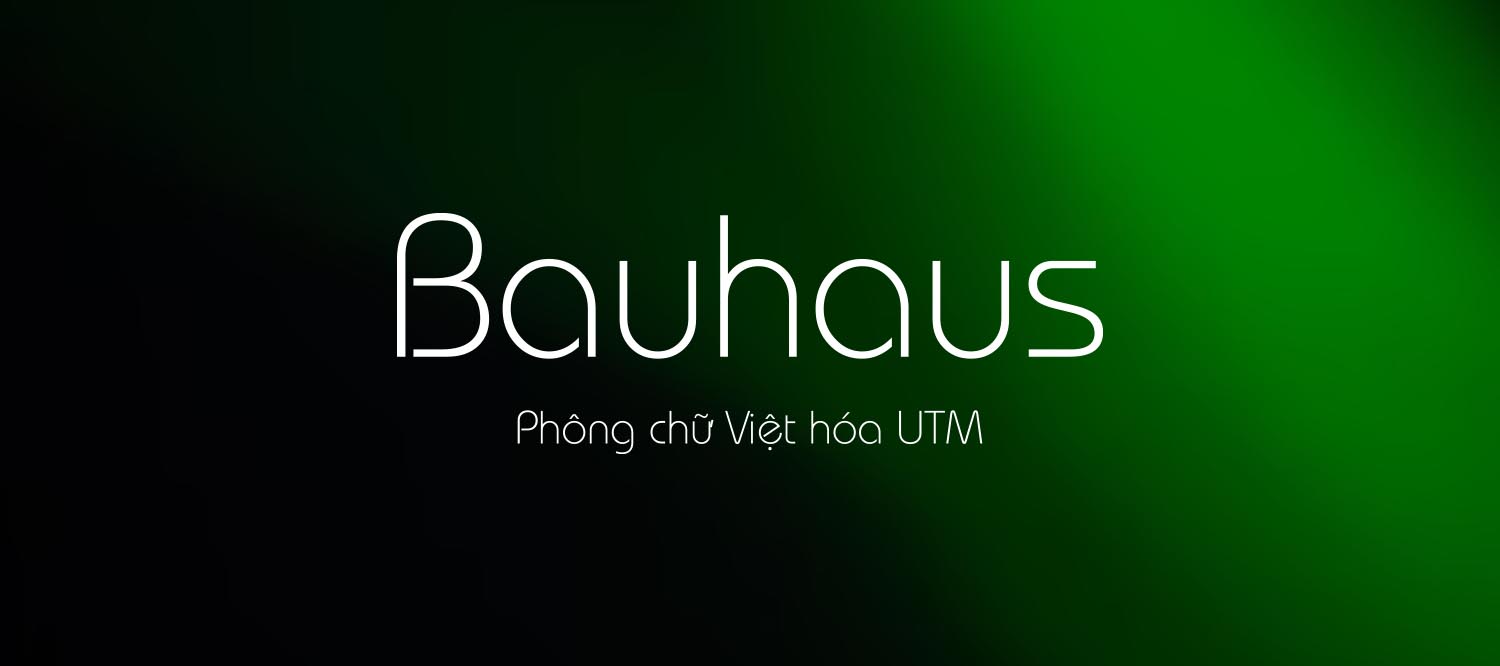
![[Tải Miễn Phí] Font Chữ Bauhaus Việt Hóa Chuẩn](https://cdn.s99.vn/cloud/font-chu-UTM-Bauhaus-Light-viet-hoa-anh-5.jpg)
Phong trào thiết kế Bauhaus xuất hiện vào đầu thế kỷ 20 tại Đức, được xem là cái nôi của trường phái thiết kế hiện đại. Nguyên lý của Bauhaus là tính tối giản, cân đối hình học và không trang trí rườm rà. Phong cách này đã ảnh hưởng mạnh mẽ đến thế giới typography.
Font Bauhaus mang những đặc trưng dễ nhận biết như:
Đường nét hình học: tròn, vuông, đơn giản
Cấu trúc rõ ràng, dễ đọc
Font sans-serif (không chân), hiện đại và tính ứng dụng cao
Tuy nhiên, nhiều font Bauhaus gốc chưa hỗ trợ đầy đủ tiếng Việt. Font Bauhaus Việt hóa chính là phiên bản đã được chỉnh sửa để bao gồm các dấu thanh và ký tự đặc trưng như: ă, â, ê, ô, đ... Việc Việt hóa giúp người dùng tự tin áp dụng trong các dự án thiết kế tại Việt Nam.
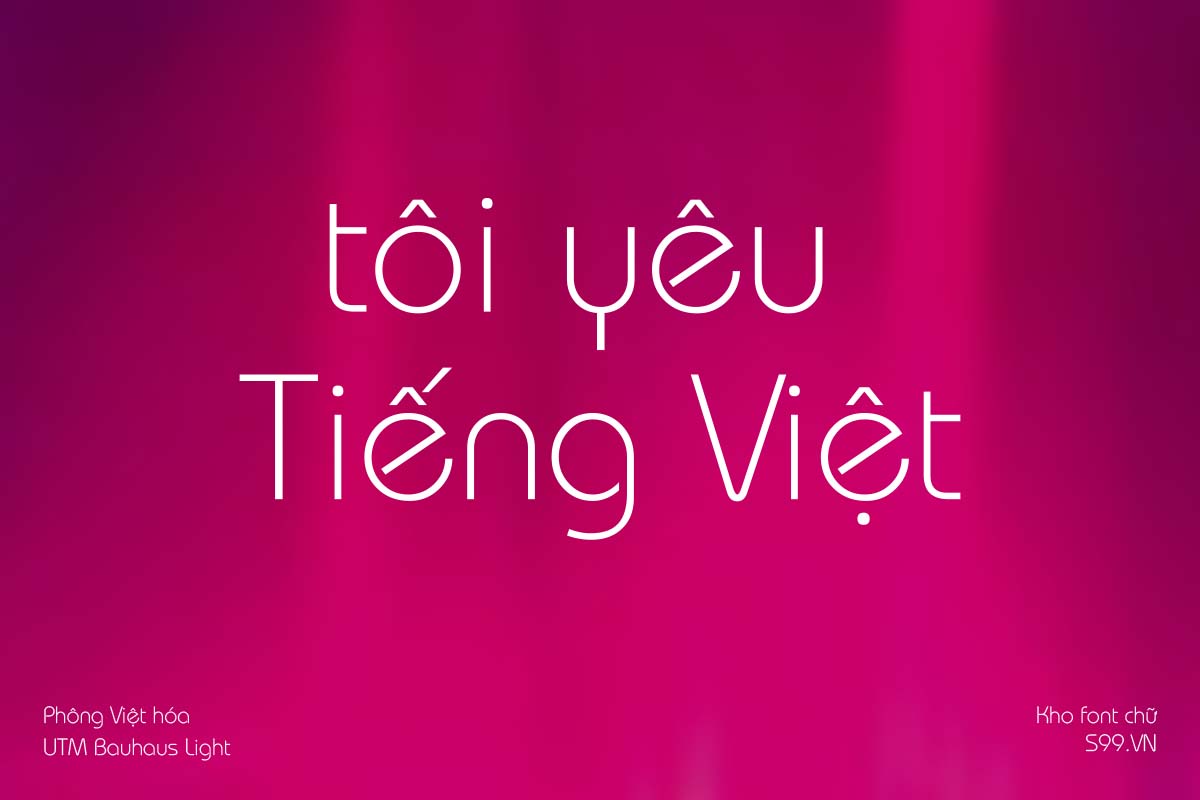
Trong thiết kế ấn phẩm tiếng Việt, việc font chữ hỗ trợ đầy đủ các dấu thanh là yêu cầu cần thiết. Phần lớn các font quốc tế chưa có hỗ trợ Unicode đầy đủ cho tiếng Việt, khi sử dụng sẽ dẫn đến các lỗi như:
Mất dấu, sai định dạng
Mất cân đối trong bố cục
Không đạt yêu cầu thẩm mỹ trong in ấn
Font Việt hóa giúp khắc phục hoàn toàn các vấn đề trên. Bằng cách thiết kế lại các dấu tiếng Việt đồng bộ với form chữ gốc, font sẽ trở nên thích hợp với người dùng Việt Nam.
Ngoài ra, một số tác giả tại Việt Nam đã thực hiện Việt hóa font Bauhaus như: Nhóm Online Fonts, Font TH của S99, SVN Fonts
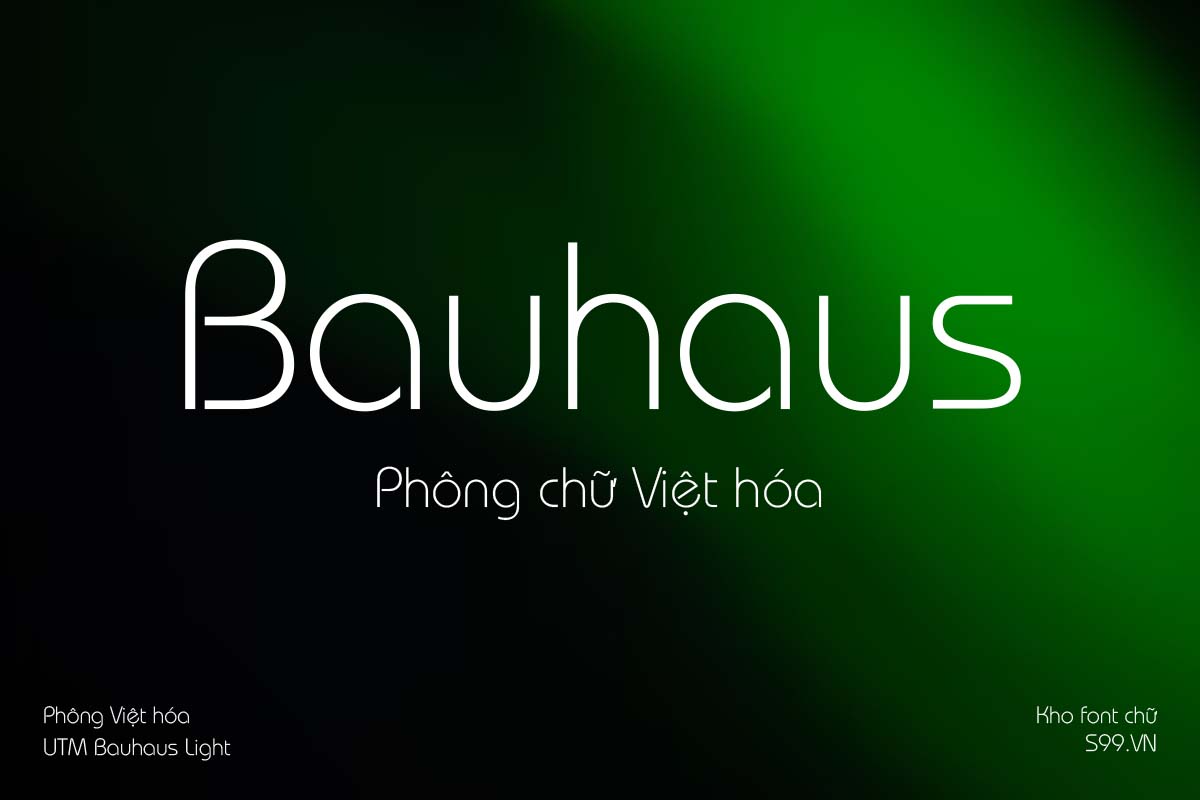
UTM Bauhaus Light là phông chữ không chân (sans-serif) mang đậm tinh thần hình học tối giản của trường phái Bauhaus. Với thiết kế gọn gàng, độ đậm nhẹ và đường nét tròn đều, font này rất lý tưởng cho các tiêu đề, logo giáo dục hoặc thiết kế mang tính học thuật. Bản Việt hóa hỗ trợ đầy đủ dấu tiếng Việt, đảm bảo hiển thị chính xác và đồng bộ trong mọi nền tảng.
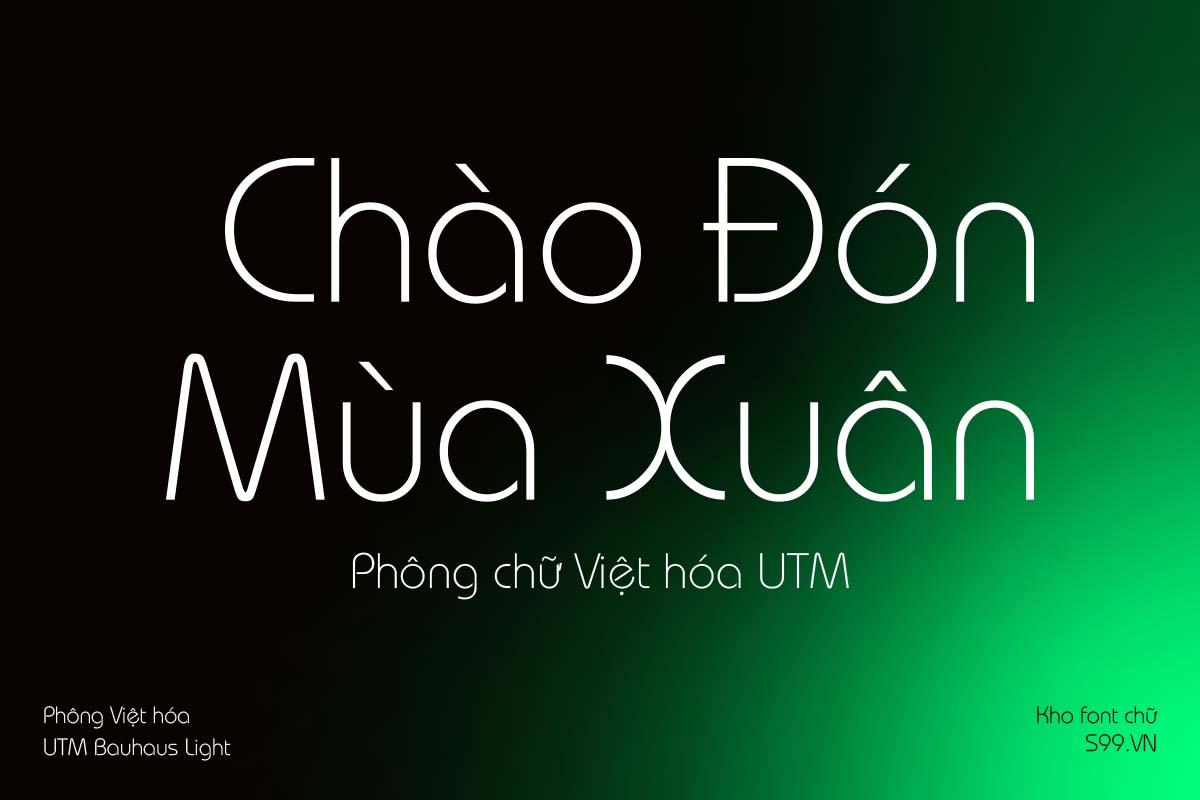
TH Cungcap 11 là font chữ mang cảm giác cứng cáp, mạnh mẽ với form dáng góc cạnh và cấu trúc hình học đậm nét. Font đặc biệt phù hợp với thiết kế poster quảng cáo, tiêu đề game hoặc banner giới thiệu sản phẩm công nghệ. Dù có dáng vẻ công nghiệp, font vẫn giữ được sự rõ ràng và cân đối khi dùng tiếng Việt.
TH Guton là bộ font hiện đại gồm 4 kiểu chữ: Regular, Medium, Bold và Black. Thiết kế dựa trên cấu trúc hình học rõ ràng, font giữ được sự cứng cáp nhưng vẫn mềm mại, thích hợp cho thiết kế UI/UX, in ấn tạp chí, và thương hiệu startup. Việt hóa hoàn chỉnh giúp đảm bảo độ tương thích cao trong mọi nội dung tiếng Việt.
TH Futurama sở hữu thiết kế hiện đại, khỏe khoắn, với các đường cắt sắc nét, phù hợp với lĩnh vực thể thao, giải trí, hoặc công nghệ. Font kết hợp giữa phong cách Bauhaus và yếu tố công nghiệp, mang lại cảm giác vừa chuyên nghiệp, vừa năng động. Bản Việt hóa hỗ trợ đầy đủ dấu, rất lý tưởng cho tiêu đề quảng bá.
Metropolis là font sans-serif kinh điển theo phong cách Bauhaus hiện đại, nổi bật với cấu trúc hình học rõ ràng, mạnh mẽ. Bộ font bao gồm tới 18 biến thể từ Thin đến Black, mang lại độ linh hoạt cao cho các dự án branding, editorial và website. Bản Việt hóa sắc sảo, hỗ trợ đầy đủ Unicode.
Coolvetica là phông chữ không chân mang nét vui nhộn và đậm chất retro hiện đại. Với 5 style đa dạng, font này phù hợp cho các thiết kế poster, tiêu đề pop-art, banner sản phẩm trẻ em hoặc sáng tạo. Bản Việt hóa giữ nguyên phong cách gốc, đồng thời thêm đầy đủ dấu tiếng Việt.
Quicksand là font không chân với đường cong bo tròn, ngọt ngào, mang đậm chất hoạt hình và phù hợp với thiết kế vui nhộn. Gồm 5 style từ Light đến Bold, font lý tưởng cho bao bì sản phẩm trẻ em, app học tiếng Anh, hoặc các dự án giáo dục. Bản Việt hóa rất mượt, không lỗi dấu.
TH Gibsons Two mang phong cách cổ điển – một nét giao thoa giữa retro, vintage và hiện đại. Font có hình khối rõ ràng nhưng vẫn giữ độ mềm ở các nét cong, rất phù hợp cho thiết kế tiêu đề báo, tạp chí, và poster xưa. Việt hóa chuẩn, thể hiện được cá tính hoài cổ trong tiếng Việt.
TH Morgaty là font sans-serif mang phong cách hiện đại, cứng cáp và mạnh mẽ. Với cấu trúc chắc chắn và độ đậm vừa phải, font phù hợp cho các thiết kế liên quan đến tài chính, công nghệ hoặc bất động sản. Bản Việt hóa được tinh chỉnh kỹ lưỡng, giúp font hoạt động tốt trong môi trường tiếng Việt.
Font Bauhaus Việt hóa không chỉ mang lại tính thẩm mỹ cao mà còn giúp thiết kế trở nên chính xác và chuyên nghiệp hơn trong ngôn ngữ tiếng Việt. Việc sử dụng các bộ font đã được Việt hóa chuẩn giúp bạn tự tin hơn khi thiết kế logo, giao diện hay ấn phẩm quảng cáo.